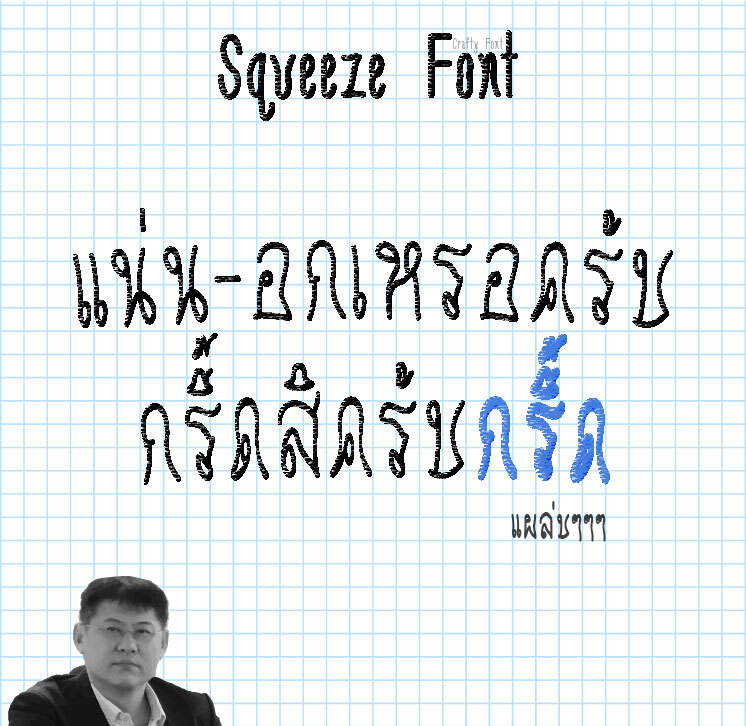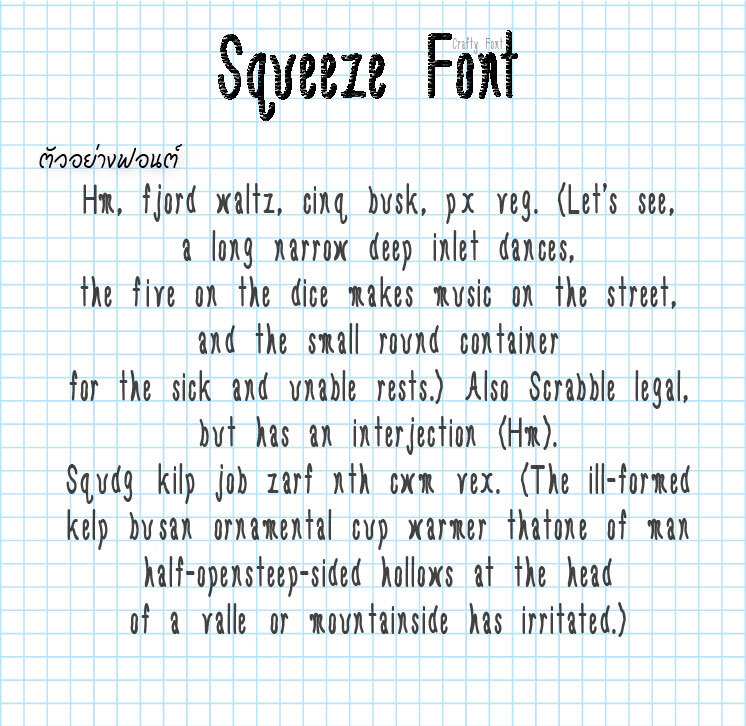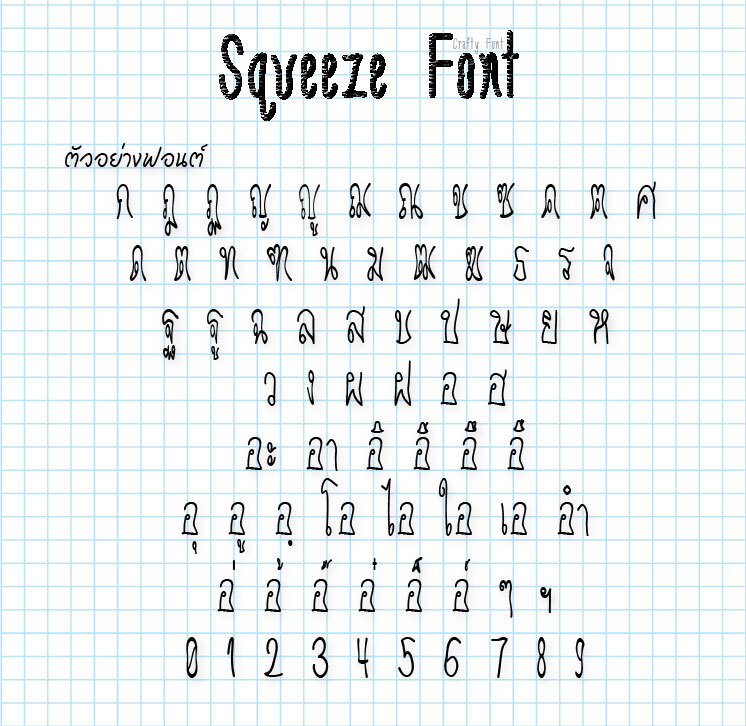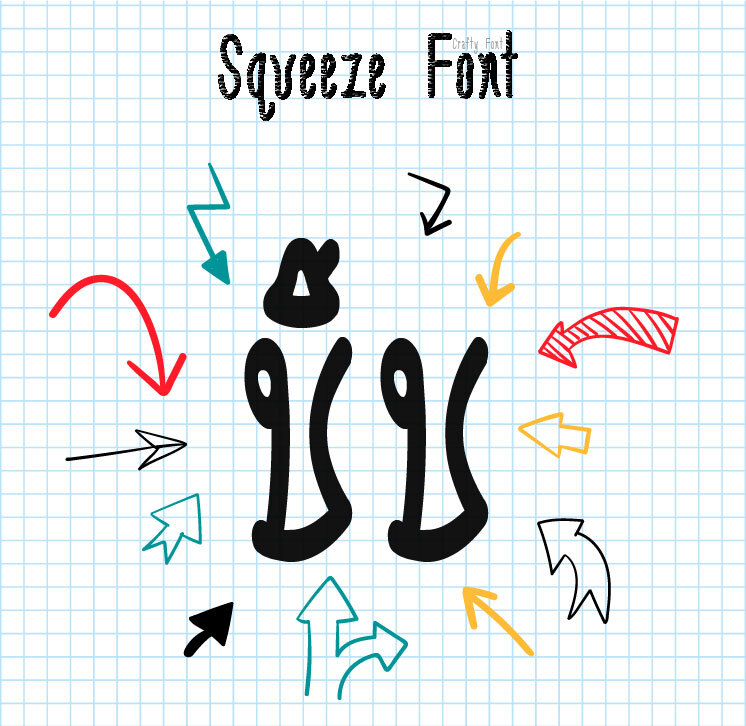
Squeeze Font (ฟอนต์บีบ)
ฟอนต์ Squeeze ฟอนต์ที่ถูกออกแบบให้โดนบีบบบบบบบบบบบ
ฟอนต์มีทั้งภาษาไทยและภาษาอังกฤษ แฟมิลี่เซ็ตนี้มี 6 ขนาดด้วยกัน ทั้งตัวหนา ตัวปกติ ตัวบาง และตัวเอนสำหรับทุกน้ำหนัก สัญลักษณ์บวกลบคูณหารมีให้ใช้ครบ ฝากไว้ในอ้อมอกอ้อมใจพี่จ๋าด้วยนะจ๊ะ